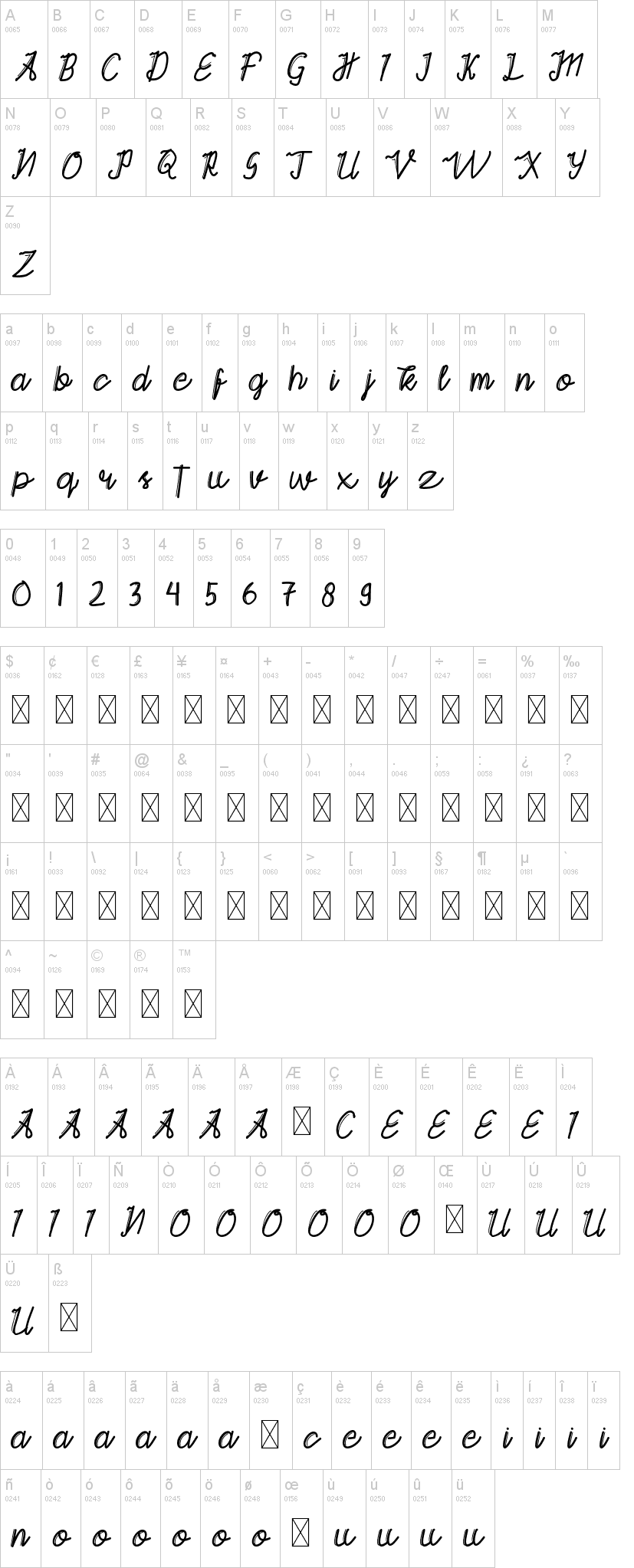
Gayatri Script 字体是一种手写风格的印度字体,由Rajendra Bitling在2001年创建。它是一种非常优美的字体,适用于印度语言,如印地语、马拉雅拉姆语、泰卢固语等。Gayatri Script 字体的字形流畅自然,具有柔软的线条和优雅的曲线,使得它适合用于印刷品设计、插图和书写。这种字体的使用范围广泛,可用于印刷材料、广告、书籍、杂志、电视、电影和其他多种媒体形式。内容介绍
Gayatri Script是一款非常不错的手写艺术字体,具有很好的视觉感,适合于文化类的宣传设计、商业类品牌的广告和产品包装设计以及个性化文字排版等较多场景。